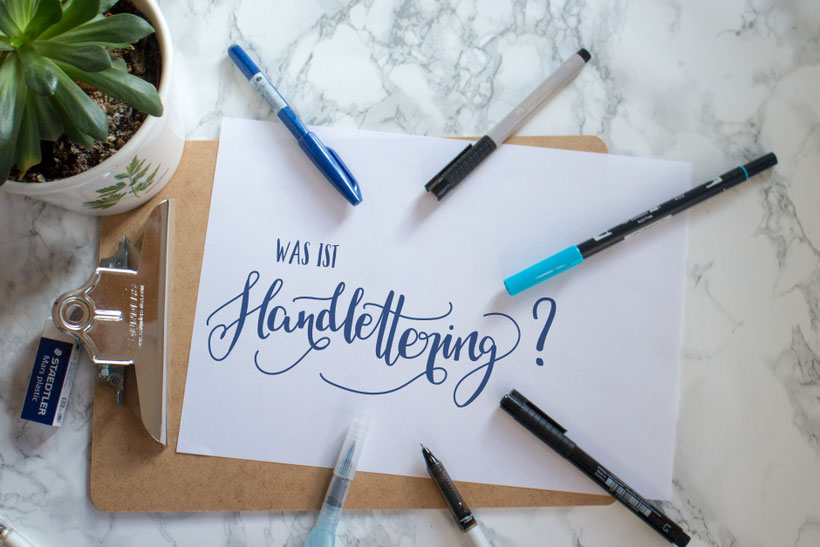
Handlettering ist die Kunst des schönem Schreibens und für mich eine Form der modernen Kalligrafie.
Handlettering ist schwer zu definieren und daran scheiden sich auch die Geister. Für mich ist es eine Unterform der Kalligrafie. Kalligrafie kommt aus dem griechischen und heißt übersetzt: kalós= schön Grafie= zeichnen/schreiben, also schönes schreiben oder zeichnen und ist somit eine Kunstform die schon seit vielen Jahrhunderten, sogar Jahrtausenden besteht.
Beim Handlettering gestaltet man eher einen schönen Spruch, Zitat oder Wort. Bei der klassischen Kalligrafie hat man eher ein festgelegtes Alphabet und man schreibt meistens längere Texte.
Kalligrafie wird im deutschsprachigem Raum klassischerweise mit Schreibfedern in Verbindung gebracht. Es gibt aber zum Beispiel im asiatischen Raum seit Jahrhunderten Kalligrafie, die dort mit Pinsel und Tusche durchgeführt wird. Man kann also Kalligrafie nicht auf ein Schreibmaterial reduzieren.
Brushlettering (Brush = englisch für Pinsel) wird mit einer beweglichen Pinselspitze gelettert. Typischerweise sind das Fasermaler, es gibt jedoch auch Stifte aus anderen Materialien.
Handlettering ist der Überbegriff. Man kann Handlettering nämlich nicht nur mit Pinselspitzen sondern auch z.B. mit Buntstiften oder Bleistiften machen! Weitere Infos zu den unterschiedlichen Stiften findet ihr auch hier.
Das Tolle an Handlettering ist: es sind alle Materialien erlaubt die euch einfallen! Filzstifte (auch Brush Pens genannt), Federhalter, Buntstifte, Kreide, Pinsel, ja sogar auf Schnee oder Sand kann man lettern!
Das macht den Einstieg für Anfänger so einfach, denn im Gegensatz zur klassischen Kalligrafie, gibt es viel weniger starre Regeln. Erlaubt ist was Spaß macht und gefällt! Es gibt natürlich Schreibgeräte die Anfänger leichter zu erlernen sind als andere und die möchte ich euch gerne vorstellen :)
Ein wesentlicher Unterschied zur Kalligrafie ist jedoch, dass es beim Handlettering eher um das Ausgestalten eines schönen Spruches oder Wort geht. Viele Sätze oder gar Seiten beschreibt man damit nicht.
Im Zuge der Digitalisierung wird heutzutage kaum mehr mit der Hand geschrieben. Vielleicht gerade deswegen, ist Handlettering oder die moderne Kalligrafie gerade auch wieder so spannend! Man schafft mit den Händen etwas und nimmt sich die Zeit bewusst etwas zu schreiben. Obwohl schreiben wohl eher der falsche Ausdruck ist. Es ist eher eine Form des Zeichnens. Denn mit der eigenen Handschrift hat Handlettering nichts zu tun.